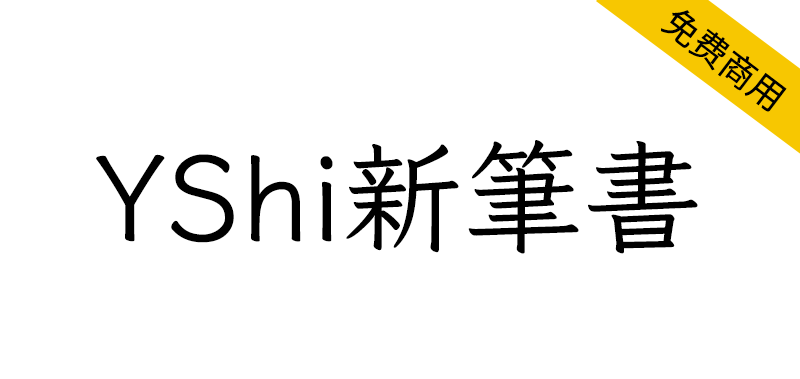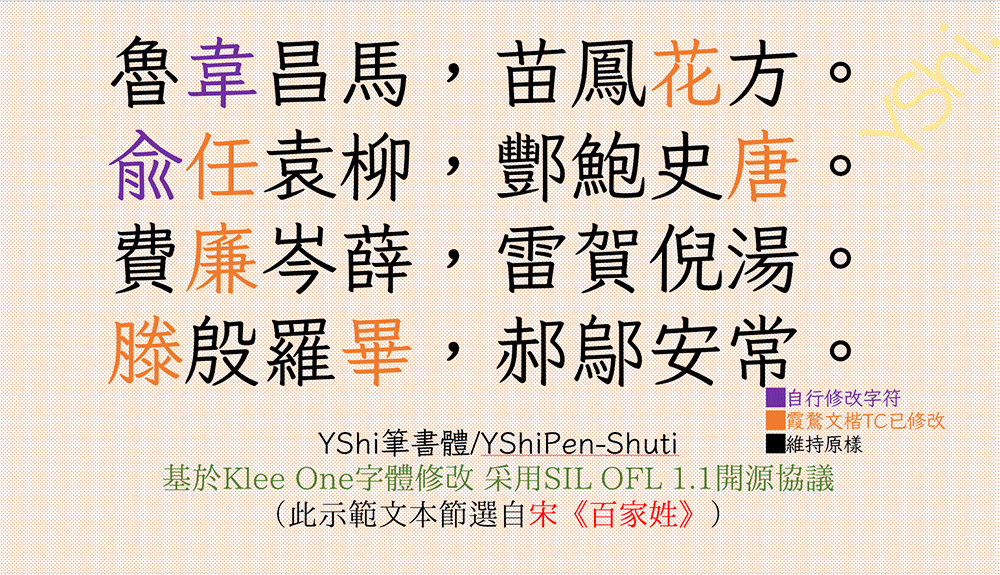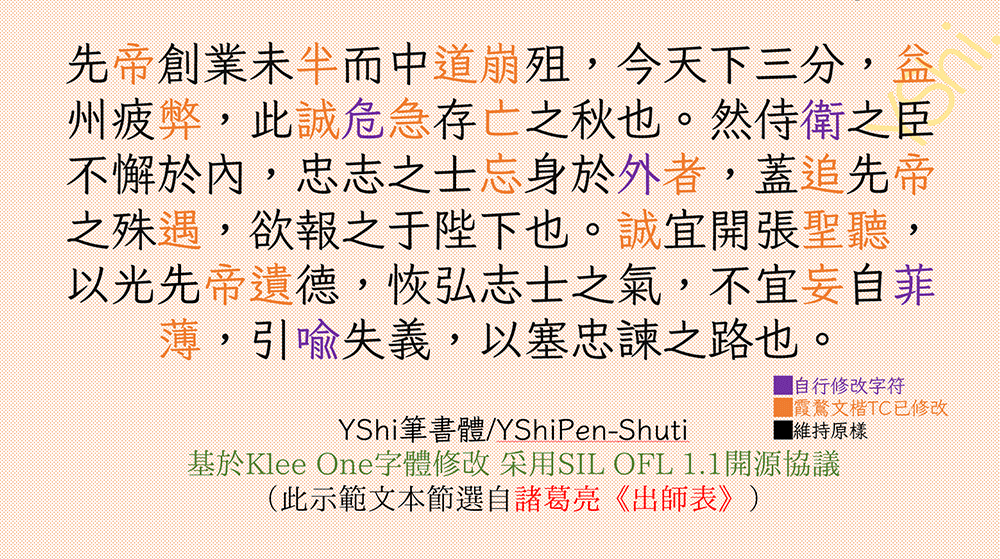
2020 年 12 月,日本著名字体厂商 FONTWORKS 在 GitHub 上释出了 7 款开源日文字体,其中 Klee One 字符数最多,兼有仿宋和楷体的特点,具有优雅的外观及较高的可读性,非常适合正文排版。此外,该字体拥有多种衍生版本,提供了更多对字形的选择性,以及增加了更多字符, 然而,仍然或多或少缺字, 此外,对于字形的选择,这些字形也不能满足所有人的口味。
YShi笔书体(YShiPen-Shuti)是基于 Klee One 进行字符扩展及补充的项目。该项目于2022 年 12 月试运行,于23年夏天正式发布第一版,起初目的是修改成偏向于康熙、98细明体标准的字形,并对Klee、霞鹜文楷TC进行扩充,主要是囊括基本区更多字符(不直接使用文楷原版炼丹的字符,而是手拼)且以旧字形展现。
本字体不严格遵循《传承字体检校表》推荐写法,而是对其进行取舍
本字体异体版少许借用碑帖中的某些异体字